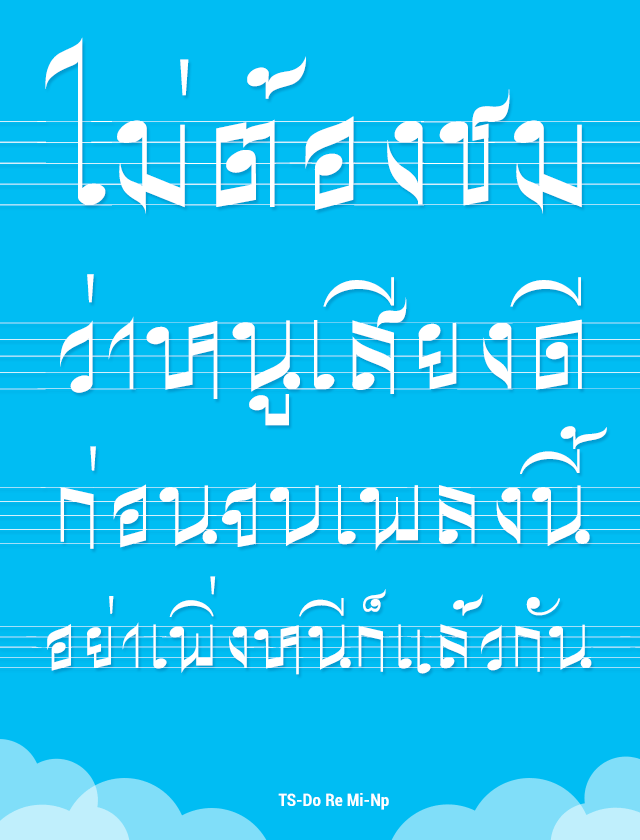
ฟอนต์แบบนี้ทำมายาวนานนับ 10 กว่าปี คือเขียนแบบแล้วก็ไม่ชอบ ก็เลยดองไว้ตั้งแต่ยังไม่มีเมีย (มัวหลงระเริงไปกับบางอย่าง) มาเสร็จสมอารมฌ์หมายเอาตอนเมียทิ้งจนเฉาไปหลายปี มันกระตุ้นต่อมความทำอยากได้ดี ก็เห็นเด็กๆ มันชอบดนตรีก็เลยขุดขึ้นมาทำต่อ เสร็จแล้วก็ไม่รู้จะได้ใช้ตอนไหน เด็กๆ คงชอบ โด เร มี โดเรมีซ่อนลา เอาฮา ฮา.. :49:
TS-Do Re Mi-NP